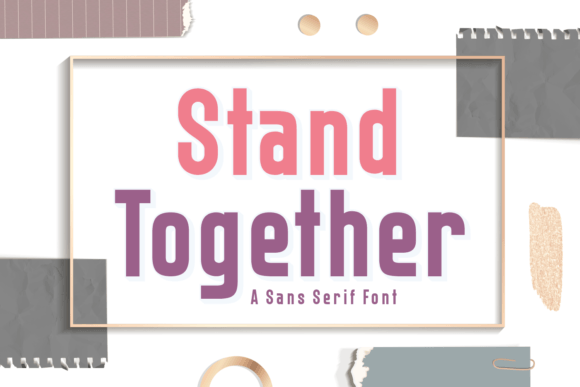
Stand Together
Att hitta rätt designelement kan vara utmanande, men Stand Together erbjuder en exceptionell samling som omedelbart lyfter ditt arbete.
Oavsett om du skapar POD-produkter (Print on Demand), bröllopsinbjudningar eller grafik för sociala medier, är Stand Together ett perfekt val.